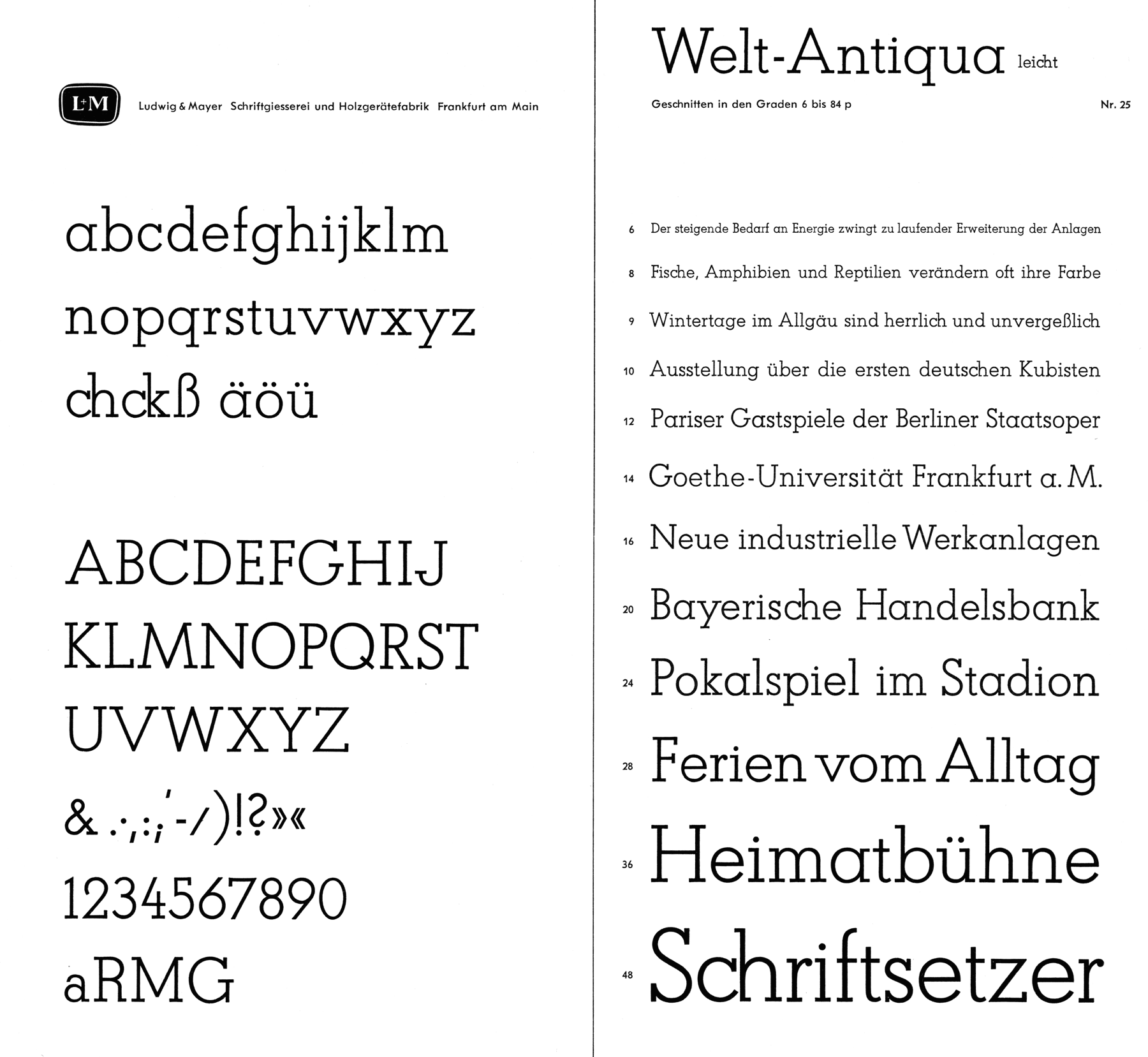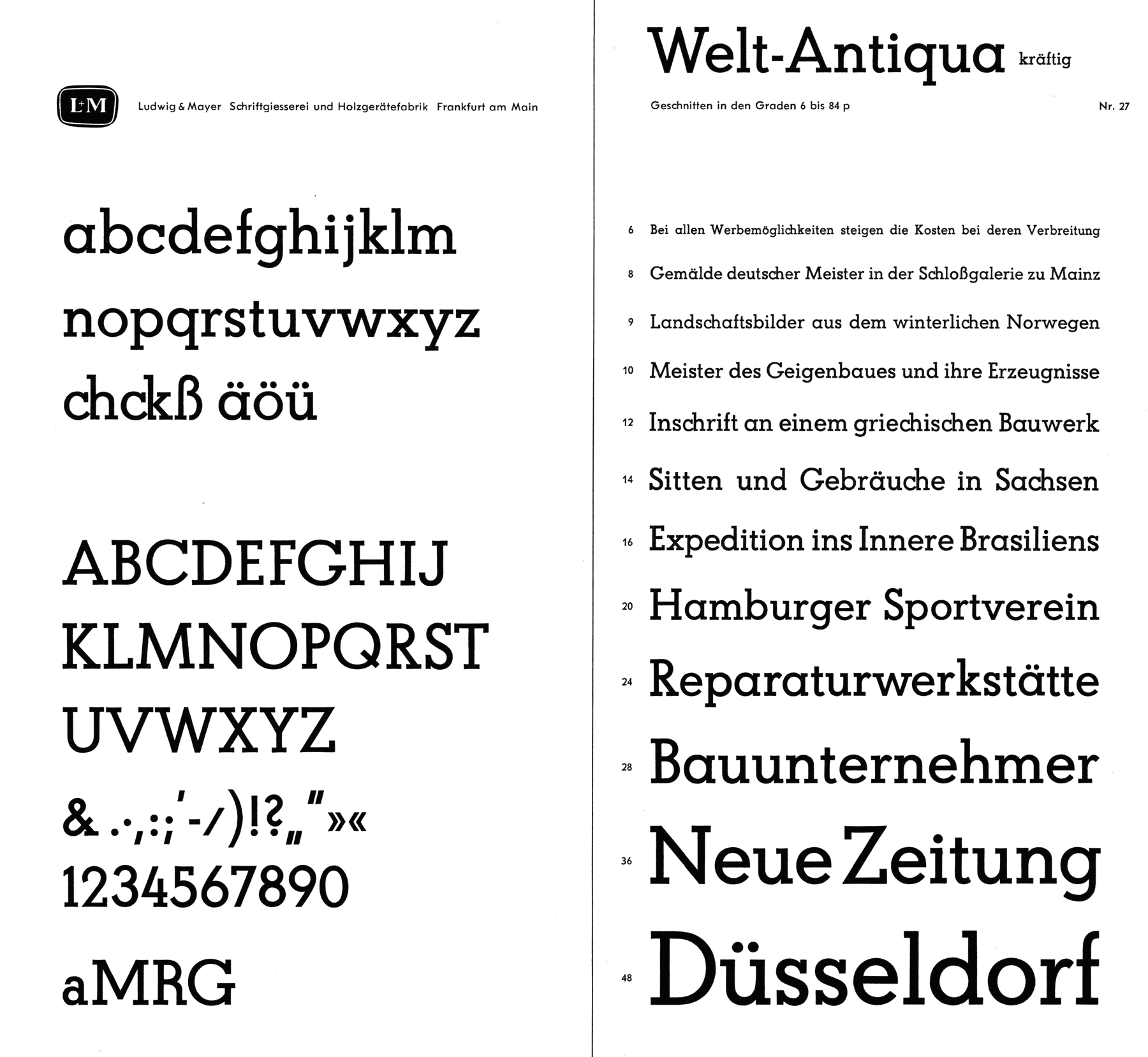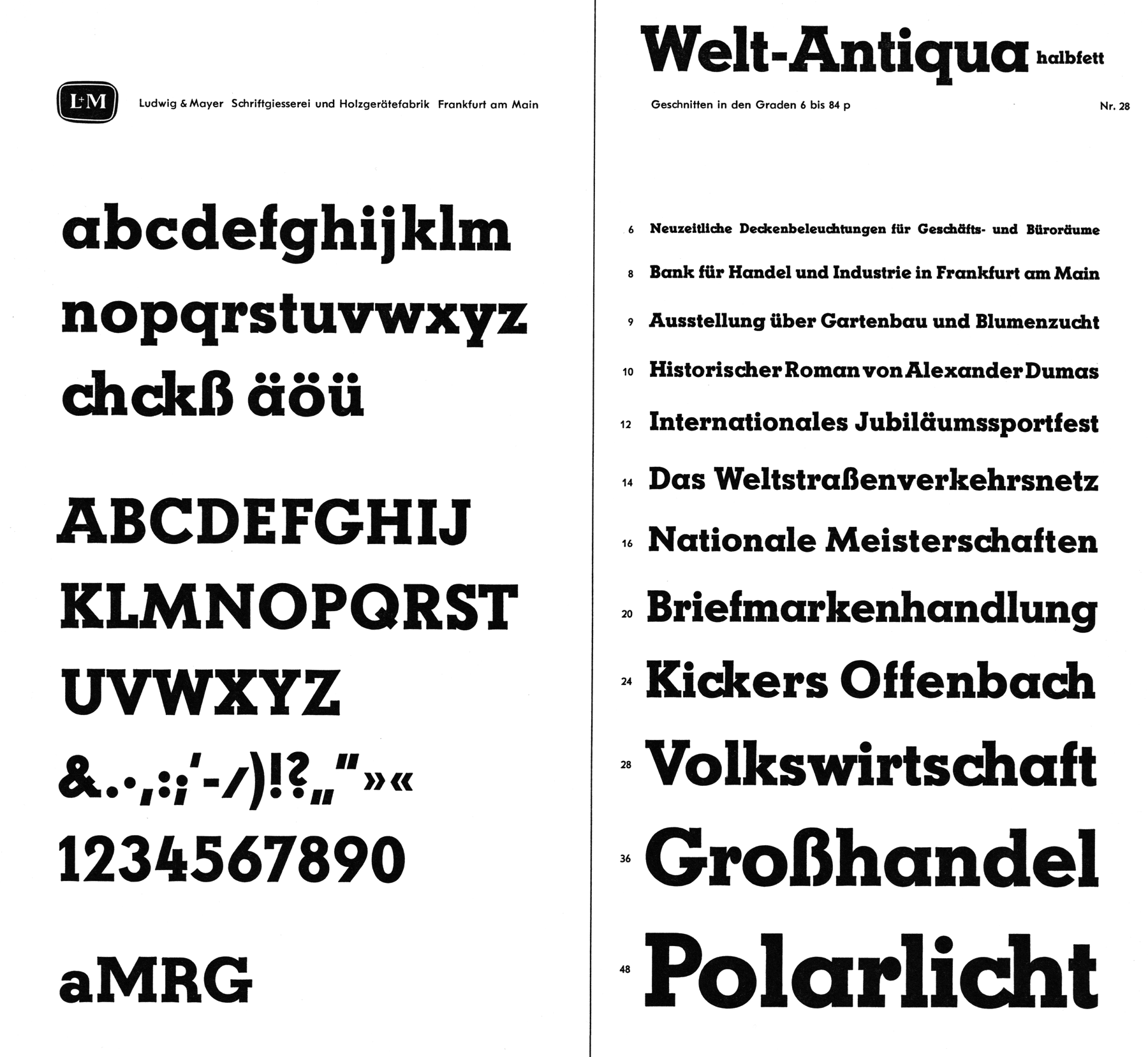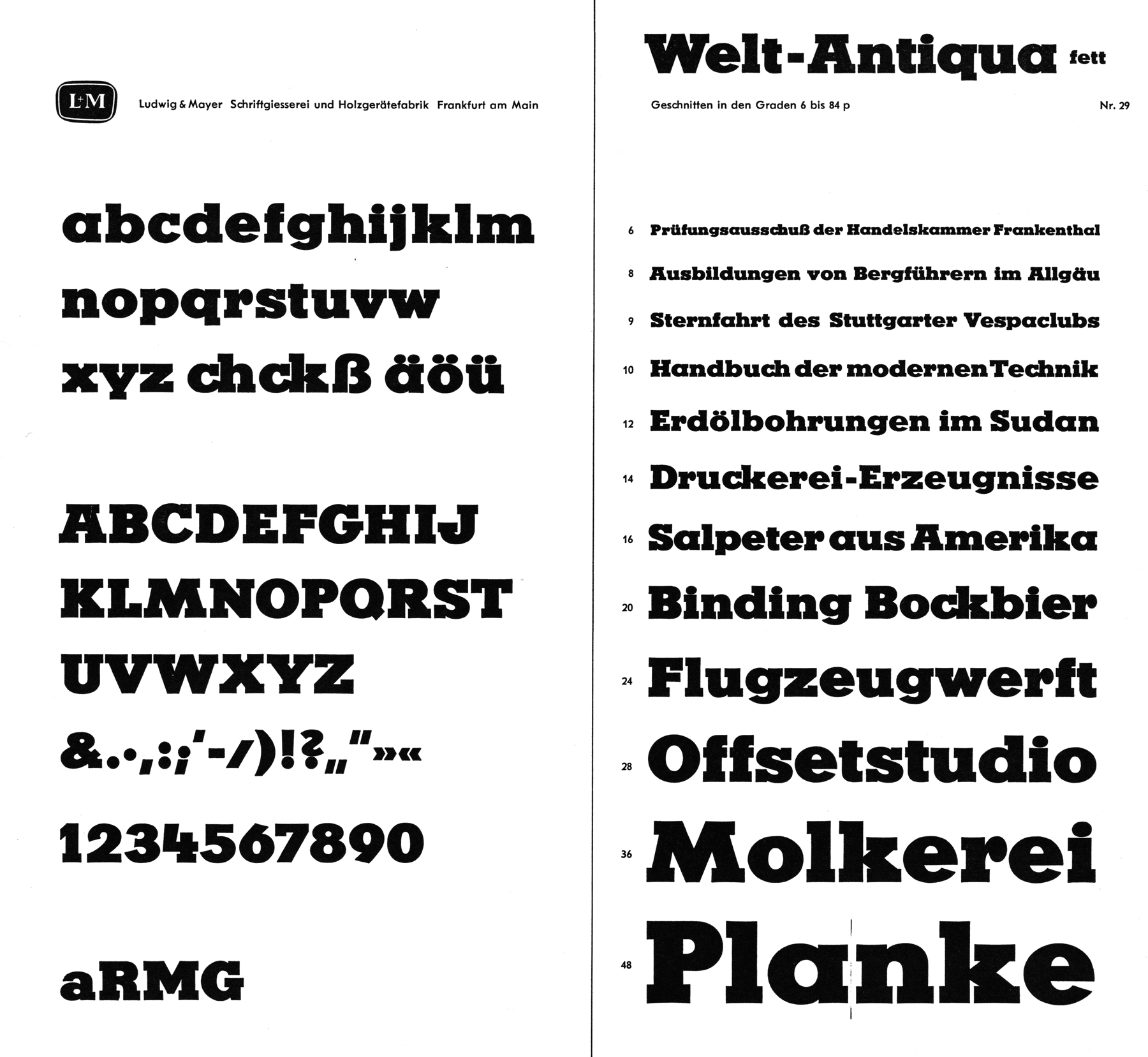
Die Welt-Antiqua ist eine serifenbetonte Linearantiqua von Hans Wagner, die in den 1930er-Jahren bei Ludwig & Wagner erschien und als »moderne, zeitgemäße und formschöne Universalschrift« beworben wurde. Die Familie wurde auf fünf lediglich aufrechte Schnitte ausgebaut. Für die Buchstaben a, M G, und R waren Varianten verfügbar.
Bei anderen Gießereien war die Schrift auch unter den Namen Luxor, Atlas, Landi, Ramsès und Ultra im Programm.